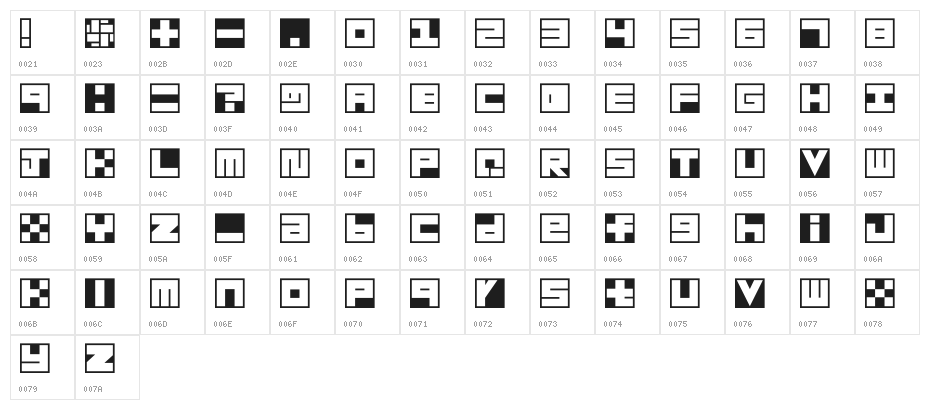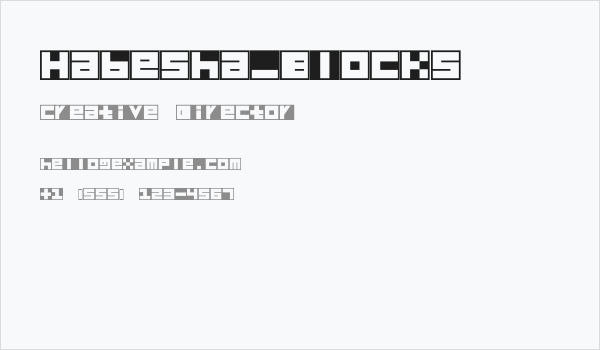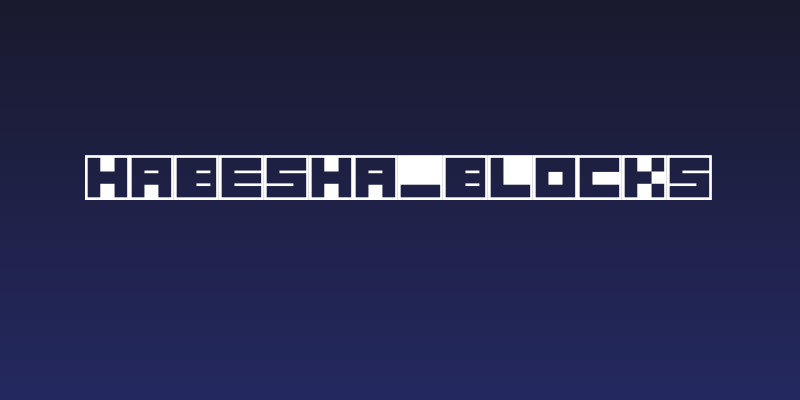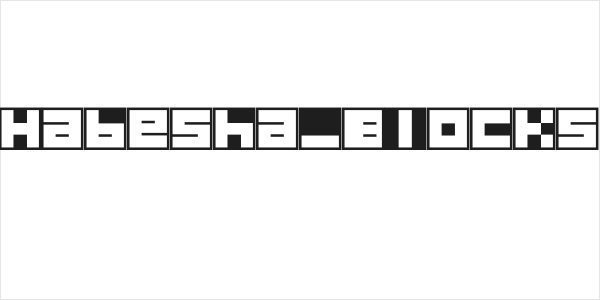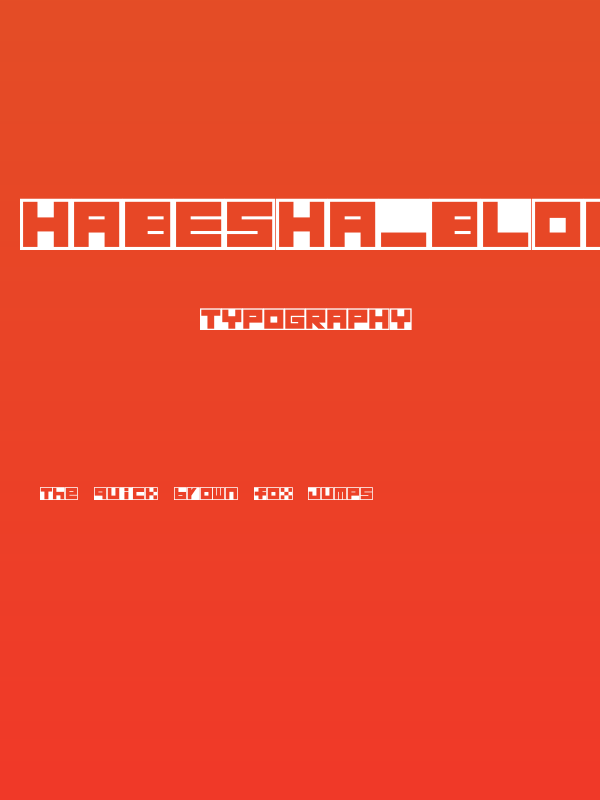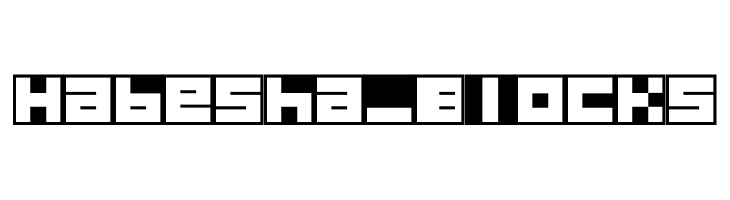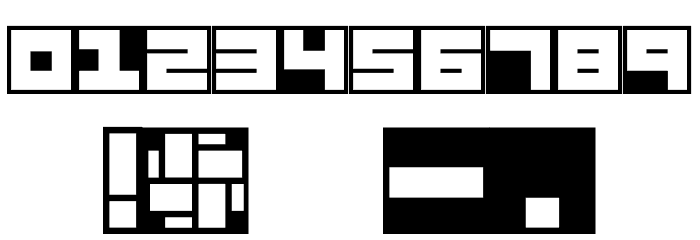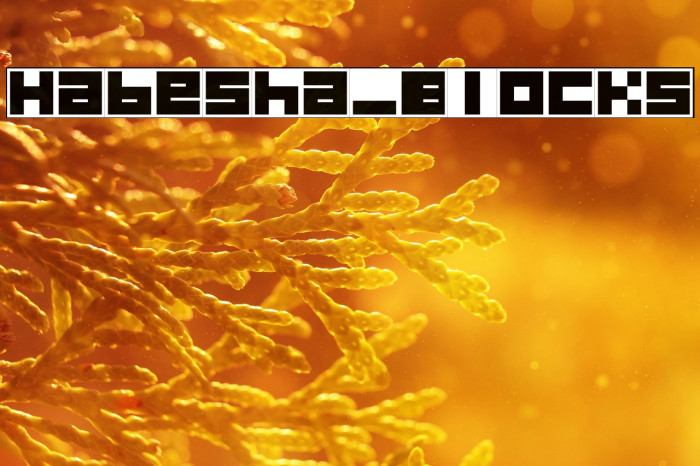
Habesha_Blocks Font
✎ Futuristic
| الفئات | Futuristic |
| حالة الاستخدام | Logos, Headlines, Posters |
| مشاريع مقترحة | Ideal for digital art, video game graphics, posters, and modern branding projects. |